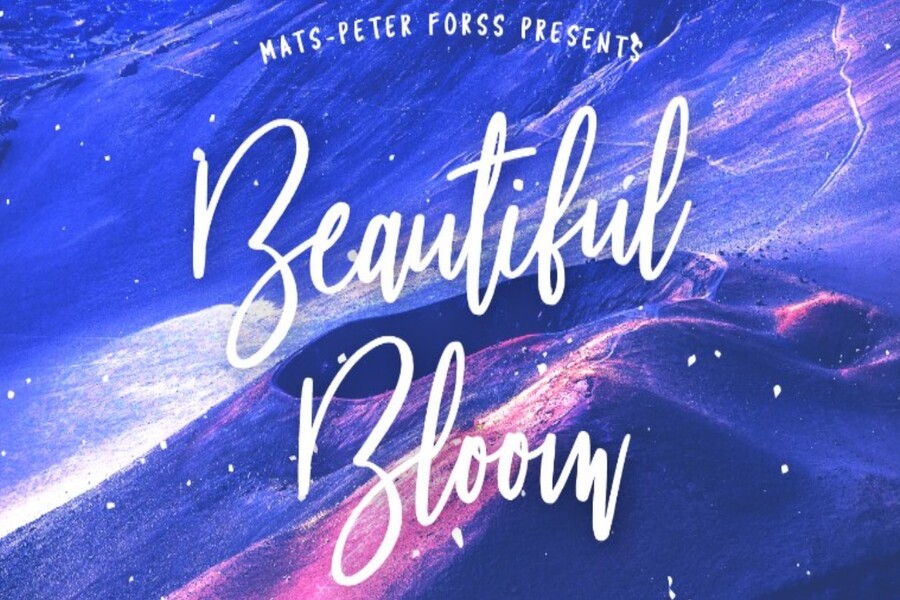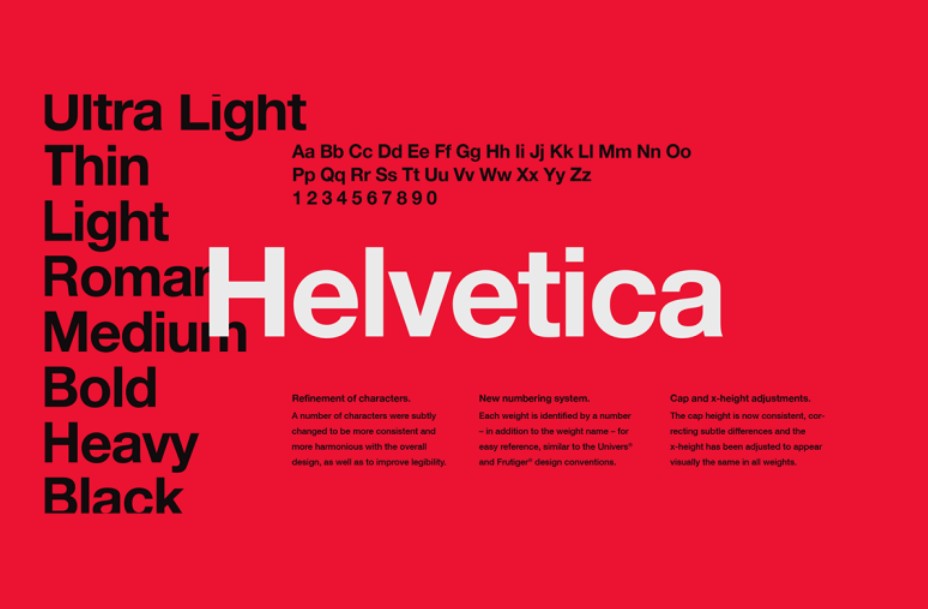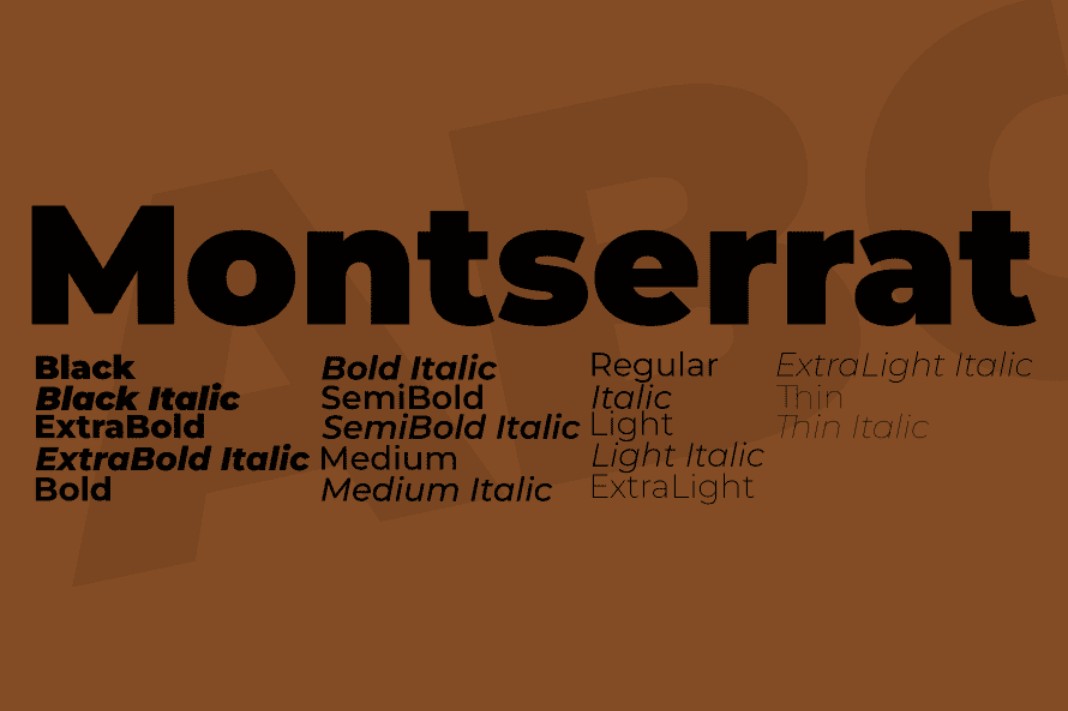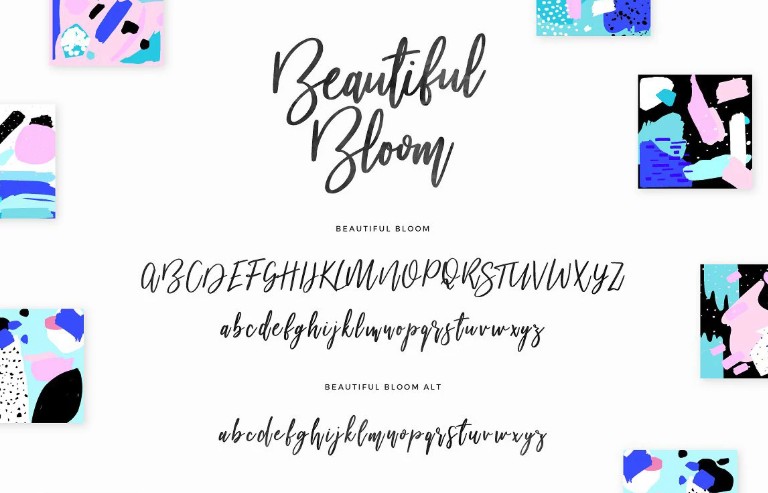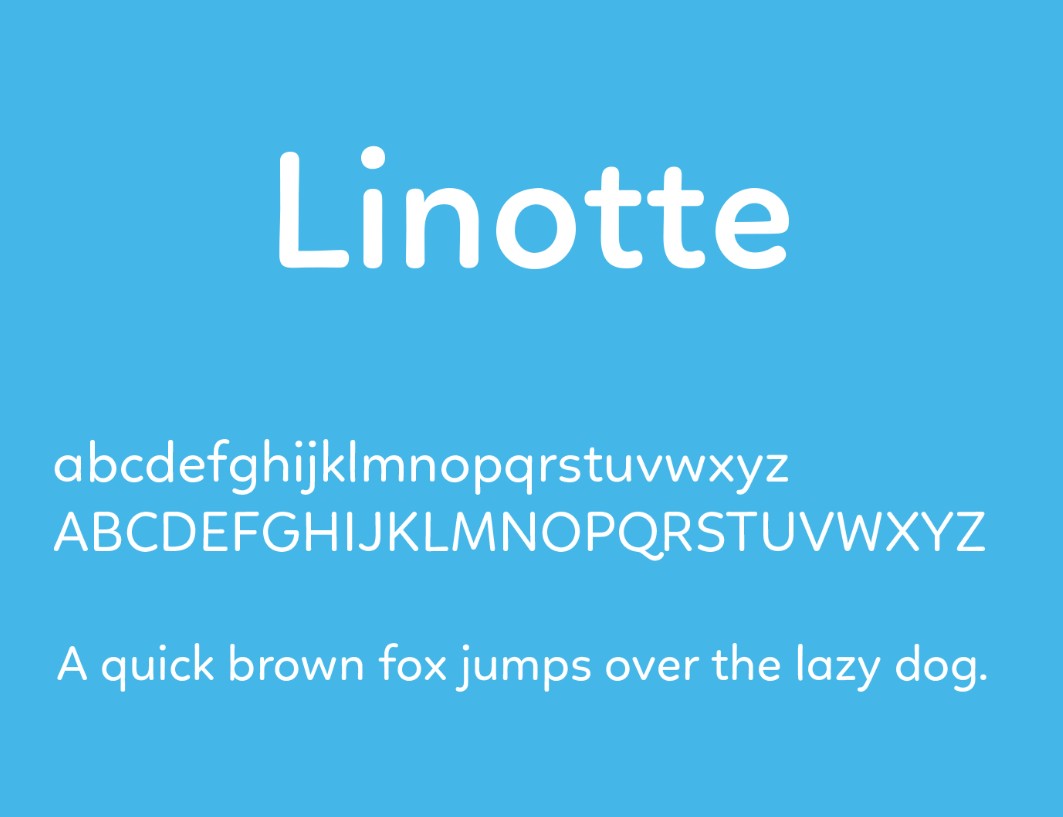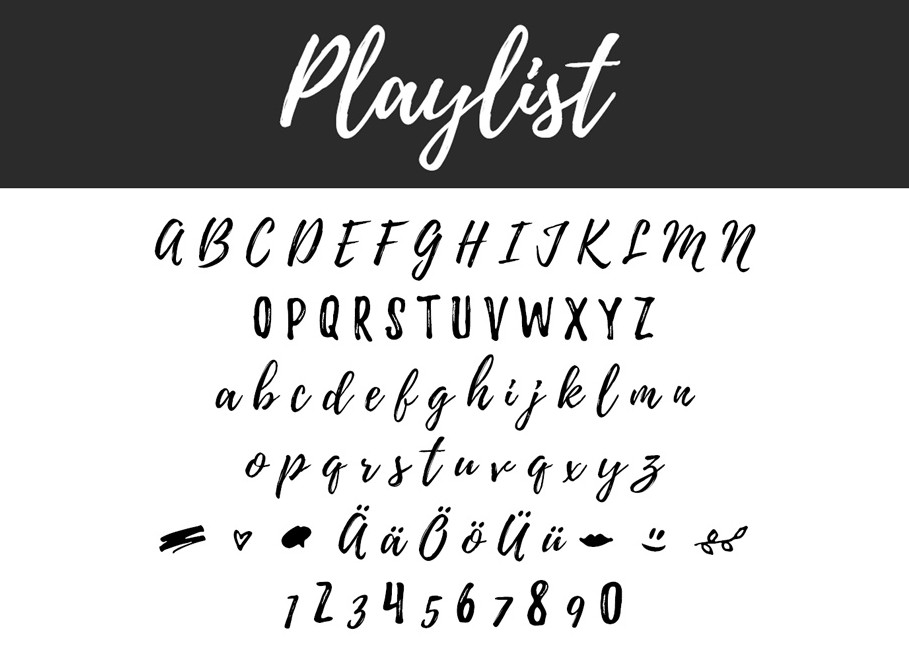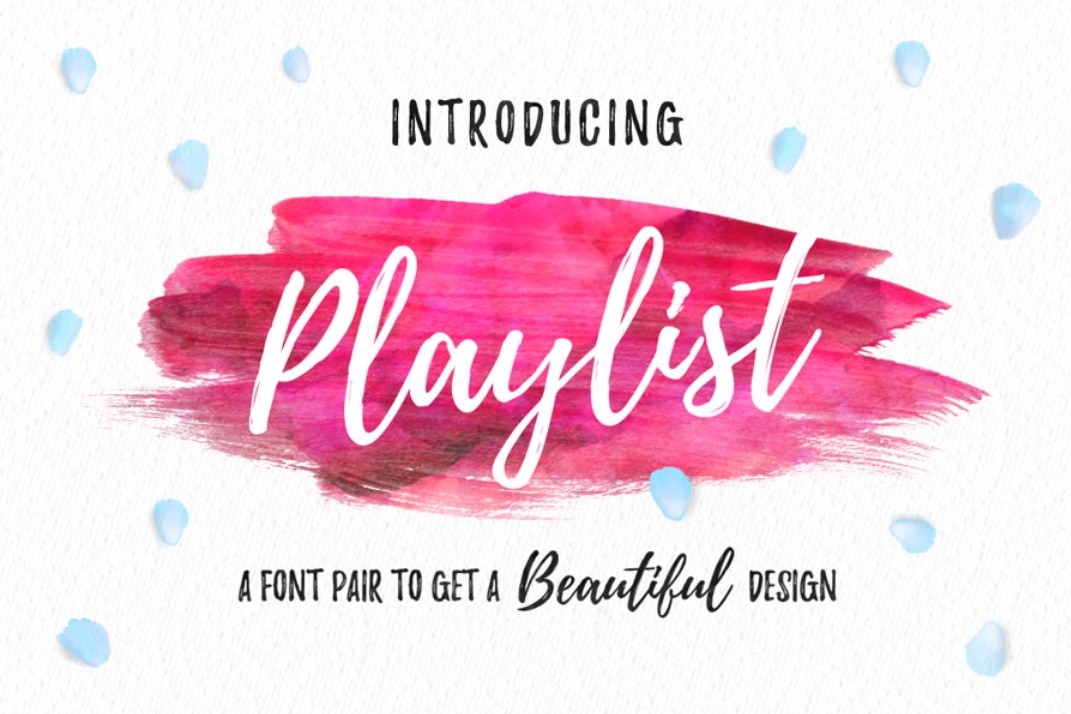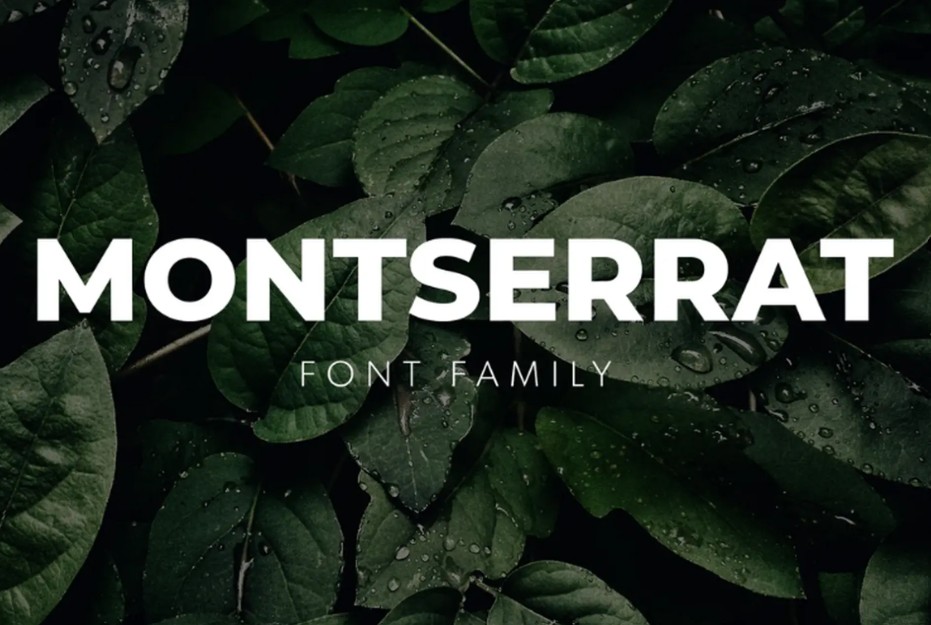
Top 5 Font Chữ Đẹp Trong Photoshop Được Designer Ưa Chuộng
Font chữ là yếu tố quan trọng giúp nâng cao thẩm mỹ và truyền tải thông điệp hiệu quả trong thiết kế Photoshop. Việc lựa chọn đúng font không chỉ giúp bố cục hài hòa mà còn tạo dấu ấn riêng cho sản phẩm.
Trong thiết kế đồ họa, hình ảnh có thể thu hút ánh nhìn nhưng chính typography mới là yếu tố giữ chân người xem và truyền tải thông điệp một cách rõ ràng, tinh tế. Đặc biệt khi làm việc với Adobe Photoshop, việc lựa chọn font chữ phù hợp không chỉ giúp nâng cao tính thẩm mỹ mà còn quyết định trực tiếp đến cảm xúc và hiệu quả truyền thông của sản phẩm. Một thiết kế đẹp nhưng dùng sai font có thể trở nên rối rắm, thiếu chuyên nghiệp, trong khi một font chữ đúng lại có thể “nâng tầm” toàn bộ bố cục chỉ trong tích tắc. Vì vậy, hiểu về font chữ và biết cách lựa chọn font phù hợp là kỹ năng quan trọng đối với bất kỳ designer nào, từ người mới bắt đầu đến chuyên nghiệp.
1. Tìm hiểu về Font chữ
Font chữ hay còn gọi là typeface là tập hợp các ký tự bao gồm chữ cái, số, dấu câu và các ký hiệu được thiết kế theo một phong cách nhất định. Trong thiết kế đồ họa, font chữ không chỉ đơn thuần là công cụ hiển thị văn bản mà còn mang tính biểu đạt cao, giúp truyền tải cá tính thương hiệu và thông điệp của sản phẩm một cách rõ ràng và nhất quán. Khi làm việc với Adobe Photoshop, font chữ không chỉ đóng vai trò hỗ trợ nội dung mà còn trở thành một yếu tố thiết kế quan trọng ngang với màu sắc hay hình ảnh.
Mỗi font chữ đều có đặc điểm riêng về hình dáng, độ dày, khoảng cách và tỷ lệ, từ đó tạo ra những cảm xúc khác nhau khi người xem tiếp nhận. Ví dụ, font serif thường mang lại cảm giác trang trọng và cổ điển, trong khi sans-serif thể hiện sự hiện đại và tối giản. Font script lại thiên về sự mềm mại, nghệ thuật, còn display font thường được dùng để tạo điểm nhấn với phong cách cá tính và nổi bật. Việc hiểu rõ đặc điểm của từng loại font giúp designer lựa chọn đúng phong cách phù hợp với mục tiêu thiết kế.
Bên cạnh yếu tố thẩm mỹ, font chữ còn ảnh hưởng trực tiếp đến khả năng đọc và trải nghiệm người dùng. Một font đẹp nhưng khó đọc sẽ làm giảm hiệu quả truyền tải thông tin, đặc biệt trong các thiết kế có nhiều nội dung. Vì vậy, việc lựa chọn font cần cân bằng giữa tính nghệ thuật và tính ứng dụng để đảm bảo vừa đẹp mắt vừa dễ tiếp cận.
2. Tầm quan trọng của font chữ trong thiết kế Photoshop
Trong nhiều trường hợp, người xem sẽ đọc nội dung trước khi quan sát hình ảnh, vì vậy font chữ chính là cầu nối giúp truyền đạt thông điệp nhanh chóng và hiệu quả. Một lựa chọn font phù hợp có thể giúp tăng khả năng ghi nhớ, tạo ấn tượng mạnh và giữ chân người xem lâu hơn.
Trong môi trường làm việc với Adobe Photoshop, font chữ ảnh hưởng trực tiếp đến bố cục và sự cân bằng thị giác của thiết kế. Một font quá dày có thể làm bố cục trở nên nặng nề, trong khi font quá mảnh lại khiến nội dung thiếu điểm nhấn. Bên cạnh đó, các yếu tố như khoảng cách chữ (tracking), khoảng cách dòng (leading) hay tỷ lệ chữ cũng đóng vai trò quan trọng trong việc tạo nên sự hài hòa và dễ đọc.
Không chỉ dừng lại ở yếu tố thẩm mỹ, font chữ còn là một phần quan trọng trong việc xây dựng nhận diện thương hiệu. Mỗi thương hiệu thường gắn liền với một phong cách font nhất định để tạo dấu ấn riêng. Ví dụ, các thương hiệu cao cấp thường sử dụng font serif hoặc font mảnh để thể hiện sự sang trọng, trong khi các thương hiệu trẻ trung lại ưu tiên font sans-serif hiện đại và năng động. Sự nhất quán trong việc sử dụng font giúp tăng độ nhận diện và tạo sự chuyên nghiệp cho thương hiệu.
Ngoài ra, font chữ còn hỗ trợ phân cấp thông tin trong thiết kế. Việc sử dụng nhiều kiểu font hoặc biến thể như bold, light, italic sẽ giúp người xem dễ dàng nhận biết đâu là tiêu đề, đâu là nội dung chính và đâu là thông tin phụ. Điều này đặc biệt quan trọng trong các thiết kế như poster, banner hay bài đăng mạng xã hội, nơi thông tin cần được truyền tải nhanh và rõ ràng.
3. Các loại font chữ đẹp trong Photoshop
Dưới đây là những font chữ đẹp, phổ biến và được đánh giá cao mà bất kỳ designer nào cũng nên cân nhắc sử dụng trong các dự án sáng tạo.
3.1 Helvetica
Helvetica là một trong những font sans-serif nổi tiếng và có ảnh hưởng nhất trong lịch sử thiết kế đồ họa. Với cấu trúc chữ cân đối, rõ ràng và tối giản, Helvetica mang lại cảm giác hiện đại, chuyên nghiệp và cực kỳ dễ đọc trên nhiều nền tảng khác nhau.
Font này thường được sử dụng trong thiết kế poster, banner, giao diện website và đặc biệt là branding doanh nghiệp. Nhờ tính trung lập và linh hoạt, Helvetica có thể kết hợp tốt với nhiều phong cách thiết kế khác nhau mà không gây xung đột thị giác. Đây được xem là “lựa chọn an toàn” nhưng vẫn đảm bảo hiệu quả cao, đặc biệt phù hợp với các dự án yêu cầu sự chỉn chu và chuyên nghiệp.
Ngoài ra, Helvetica còn có nhiều biến thể về độ dày như Light, Regular, Bold, giúp designer dễ dàng tạo phân cấp nội dung mà vẫn giữ được sự đồng nhất trong thiết kế.
3.2 Montserrat
Montserrat là font chữ hiện đại, lấy cảm hứng từ phong cách typography đô thị, đặc biệt là các biển hiệu tại khu Montserrat (Argentina). Font sở hữu thiết kế hình học rõ ràng, cân đối và mang đậm tinh thần trẻ trung, năng động.
Montserrat rất phù hợp cho các dự án thiết kế kỹ thuật số như website, mạng xã hội, landing page hoặc UI/UX. Khả năng hiển thị tốt ở nhiều kích thước giúp font này giữ được độ sắc nét cả khi dùng làm tiêu đề lẫn nội dung chính. Đây cũng là một trong những font phổ biến trên Google Fonts nhờ tính miễn phí và dễ tích hợp.
Một điểm mạnh khác của Montserrat là sự đa dạng về weight và style, giúp designer linh hoạt trong việc sáng tạo bố cục và phân cấp thông tin mà vẫn giữ được sự hiện đại và đồng bộ.
3.3 Beautiful Bloom
Beautiful Bloom là font script mang phong cách viết tay mềm mại, tạo cảm giác nghệ thuật và giàu cảm xúc. Với các nét chữ uốn lượn tự nhiên, Beautiful Bloom thường được sử dụng trong những thiết kế mang tính cá nhân hóa hoặc cần yếu tố thẩm mỹ cao.
Font này rất phù hợp cho thiệp cưới, poster nghệ thuật, logo thời trang hoặc các sản phẩm liên quan đến lifestyle. Beautiful Bloom giúp tạo điểm nhấn nổi bật, mang lại cảm giác tinh tế, lãng mạn và gần gũi.
Tuy nhiên, do đặc điểm là font script, Beautiful Bloom cần được sử dụng hợp lý, tránh dùng cho đoạn văn dài vì có thể gây khó đọc. Thay vào đó, font nên được dùng cho tiêu đề, tagline hoặc các chi tiết nhấn mạnh để phát huy tối đa hiệu quả thị giác.
3.4 Linotte
Linotte là font sans-serif hiện đại với thiết kế bo tròn mềm mại, tạo cảm giác thân thiện và dễ tiếp cận. Không quá cứng như các font hình học, Linotte mang đến sự cân bằng giữa tính chuyên nghiệp và sự gần gũi.
Font này thường được sử dụng trong thiết kế bao bì, sản phẩm tiêu dùng, nội dung dành cho giới trẻ hoặc các thương hiệu hướng đến sự thân thiện với người dùng. Nhờ cấu trúc chữ rõ ràng và khoảng cách hợp lý, Linotte đảm bảo khả năng đọc tốt trong nhiều bối cảnh khác nhau.
Ngoài ra, Linotte cũng có nhiều biến thể về độ dày, giúp designer linh hoạt trong việc xây dựng bố cục và tạo điểm nhấn mà không cần sử dụng quá nhiều font khác nhau trong cùng một thiết kế.
3.5 Playlist
Playlist là font chữ mang phong cách cá tính và sáng tạo, thường được sử dụng để tạo điểm nhấn mạnh mẽ trong thiết kế. Với nét chữ độc đáo, hơi hướng handwritten kết hợp với phong cách display, Playlist mang lại cảm giác tự do, phá cách và rất phù hợp với các dự án mang tính nghệ thuật.
Font này thường được dùng cho tiêu đề poster, banner quảng cáo, thiết kế âm nhạc hoặc các chiến dịch truyền thông cần sự nổi bật. Khi sử dụng đúng cách, Playlist có thể trở thành yếu tố “signature” giúp thiết kế trở nên khác biệt và dễ nhận diện hơn.
Tuy nhiên, giống như nhiều display font khác, Playlist không phù hợp cho nội dung dài mà nên sử dụng ở các vị trí quan trọng như headline hoặc slogan. Khi kết hợp với các font đơn giản hơn, Playlist sẽ phát huy tối đa hiệu quả và tạo nên sự cân bằng trong tổng thể thiết kế.
4. Cách cài đặt font chữ đẹp vào Photoshop
Để sử dụng font chữ đẹp trong Adobe Photoshop, trước tiên bạn cần cài đặt chúng vào hệ thống của mình. Đây là bước cơ bản nhưng rất quan trọng để mở rộng thư viện font và nâng cao khả năng sáng tạo.
Bước đầu tiên là tải font chữ từ các nguồn uy tín. Bạn có thể tìm kiếm trên Google Fonts với hàng nghìn font miễn phí, dễ sử dụng và phù hợp cho nhiều mục đích khác nhau. Ngoài ra, DaFont cũng là nơi cung cấp nhiều font độc đáo, từ cổ điển đến hiện đại. Nếu bạn sử dụng hệ sinh thái Adobe, Adobe Fonts sẽ là lựa chọn lý tưởng với kho font chất lượng cao và tích hợp sẵn.
Sau khi tải về, bạn chỉ cần mở file font định dạng .ttf hoặc .otf và chọn cài đặt. Hệ thống sẽ tự động thêm font vào thư viện và Photoshop sẽ nhận diện ngay khi khởi động.
Hy vọng bài viết này sẽ giúp bạn hiểu rõ hơn về font chữ và biết cách áp dụng chúng hiệu quả trong Photoshop từ đó nâng cấp chất lượng thiết kế và tạo ra những sản phẩm ấn tượng hơn trong hành trình sáng tạo của mình.